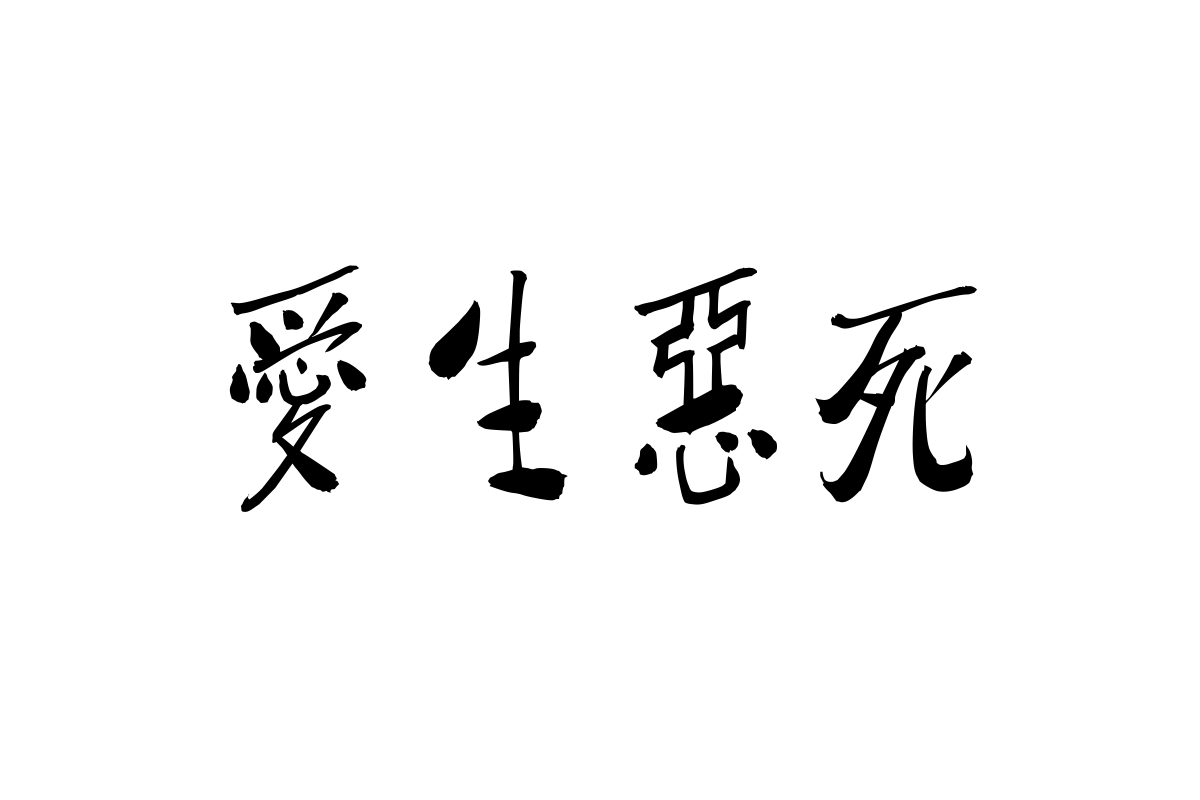
汉仪迪升花海繁体字体是一款具有现代感和艺术气息的中文字体,适用于各种商业、广告、设计等领域。这款字体的特点是字形简洁大方,线条流畅自然,给人一种清新、优雅的感觉。其特点是:
1. 字形简洁大方:汉仪迪升花海繁体字体的字形设计简洁大方,线条流畅自然,没有过多的装饰元素,给人一种清爽、简约的感觉。
2. 笔画流畅:这款字体的笔画流畅自然,没有僵硬的线条,给人一种舒适、轻松的感觉。
3. 艺术气息浓厚:汉仪迪升花海繁体字体的设计充满了艺术气息,无论是在视觉上还是触感上,都给人一种独特的美感。
4. 适用范围广泛:这款字体适用于各种商业、广告、设计等领域,无论是文字排版还是图形设计,都能展现出其独特的魅力。
总之,汉仪迪升花海繁体字体是一款具有现代感和艺术气息的中文字体,适用于各种商业、广告、设计等领域,是设计师们不可或缺的一款字体。